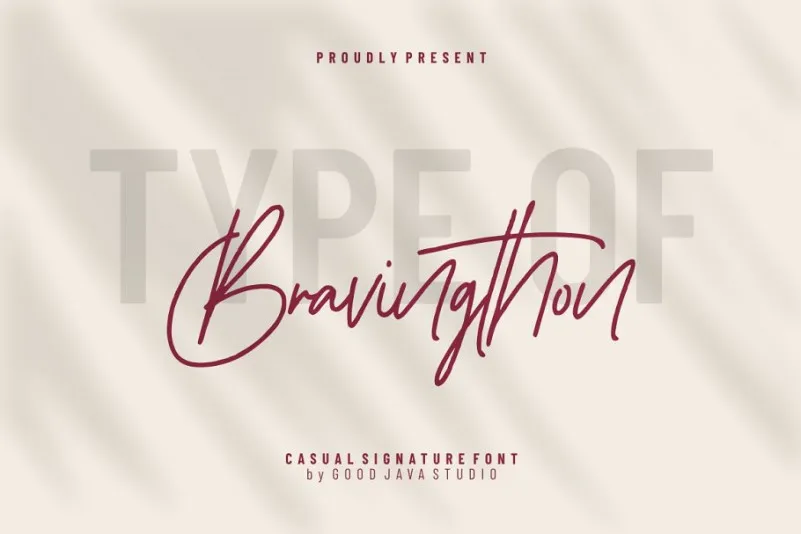
Bravingthon Signature Font
Olá! Estamos muito felizes por você estar considerando a Bravingthon Signature Font para seu projeto. Esta é uma fonte script criada a partir das digitais humanas, com um toque natural e elegante. Ela foi projetada pelo estúdio Good Java Studio. Bravingthon Signature Font é perfeitamente adequada para aplicativos que desejam transmitir um ar sofisticado e elegante. Este é um tipo de fonte escrita a mão, moderna e natural. É ideal para uso em logotipos, convites, embalagens de estação, designs de casamentos, posts nas redes sociais, anúncios, pacotes de produtos, rótulos, fotografias, marcas, eventos especiais ou qualquer outro projeto que você precise. Estamos certos de que esta fonte dará um toque único e agradável à sua marca. Sua natureza serena, combinada com seu ar moderno, o torna perfeito para uma variedade de aplicações gráficas. Experimente Bravingthon Signature Font e veja como ela pode transformar seus projetos.